1、字体视界法棍体
字体视界法棍体是由字体视界推出的首款免费字体,它将免费开放商业授权给到所有个人和企业,让所有用户可以免费使用。
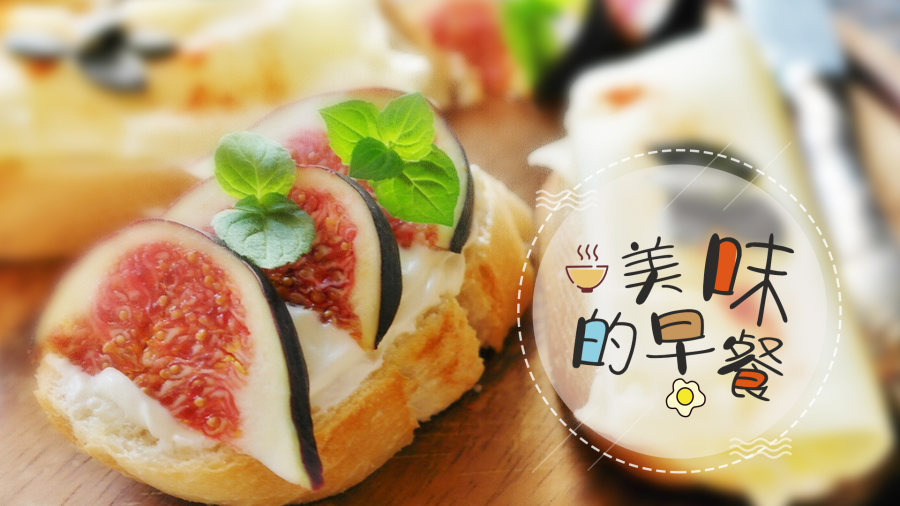
2、薯条体
麦当劳这次以金黄的薯条和必备的番茄酱为灵感,除了开放免费下载也能商业使用!
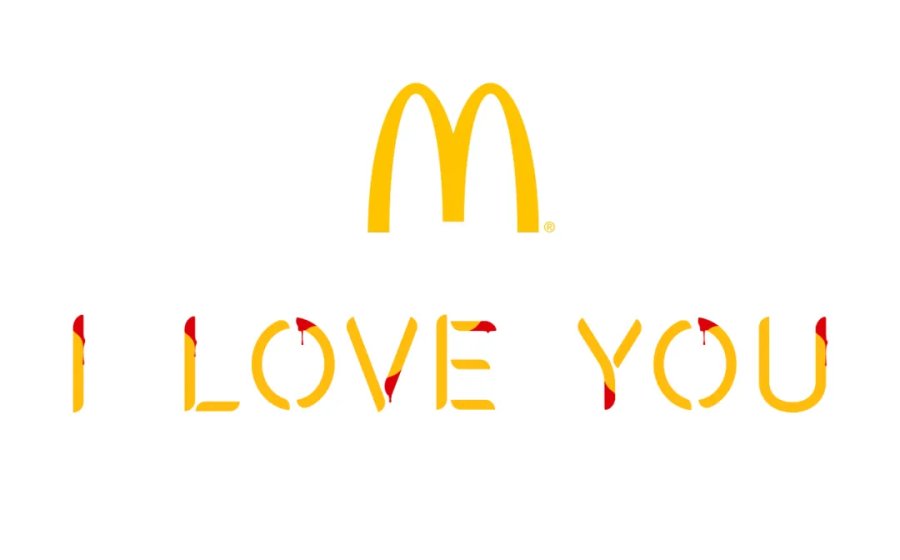
3、阿里巴巴普惠体
阿里巴巴普惠体是阿里巴巴公司发布的一款可免费商用的字体,其中收录了11.6万个汉字,7205个拉丁字母,覆盖173个语种,中文有5个字重,西文有11个字重。允许任何个人和企业免费使用,包括商用用途,但禁止用于违法用途。
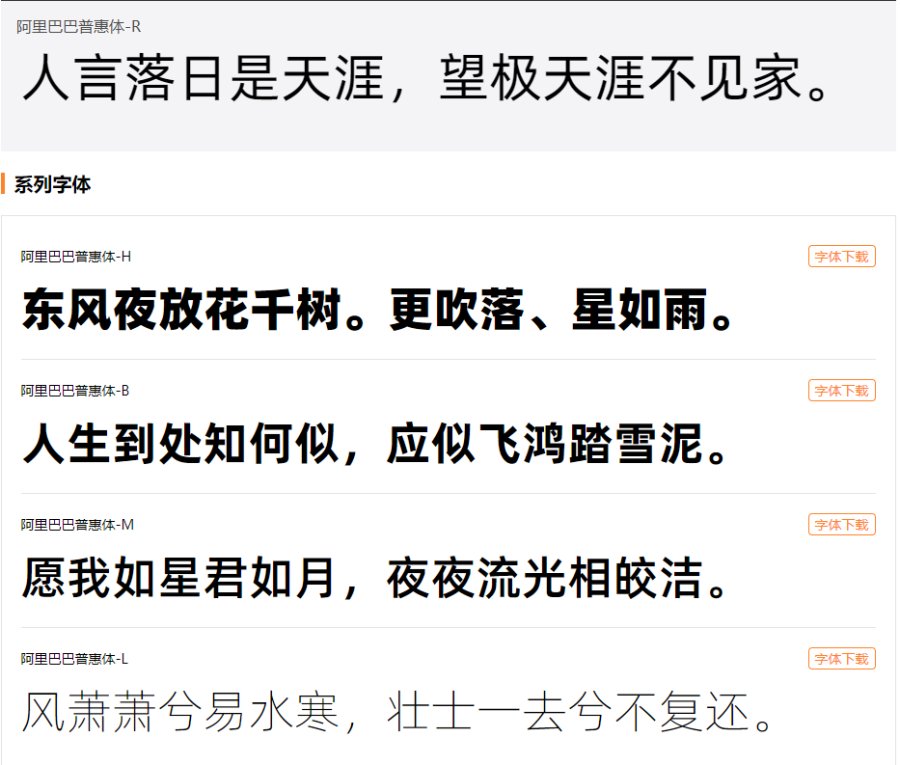
4、锐字真言体
该字体线条粗壮有力,字形大方得体,整体内外空间布局均匀,能够应用于文本装潢、信息展示、网页设计、篆刻制模、数据制作、装潢设计、计算艺术设计、视觉设计、字帖等应用场景。